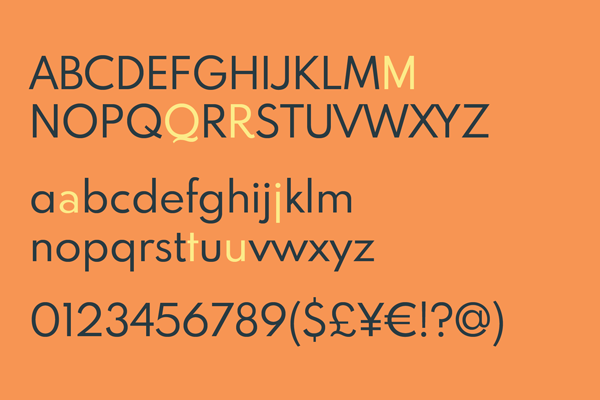
[Mitglied Vors…] Geschrieben November 9, 2019 Teilen Geschrieben November 9, 2019 Hallo! Wie findet ihr / gefällt euch die Drescher Grotesk? Ich würde sie gern für ein Cover (Ausmalbuch) verwenden, bin mir aber unsicher, da ich gelesen habe, dass sie manche wohl als Schrottschrift bezeichnet haben. Mir gefällt die Schrift jedoch sehr gut. Wem sie nicht gefällt: Was spricht gegen sie? Was mögt ihr nicht? Hier ein Link zur Ansicht: https://www.myfonts.com/fonts/bitstream/drescher-grotesk-bt/semi-bold/ Vielen Dank schon mal im Voraus! Gruß Peter Link zu diesem Kommentar
[Mitglied 1454…] Geschrieben November 9, 2019 Teilen Geschrieben November 9, 2019 Als Schrott hat sie – soweit ich weiß – nur Ulrich Stiehl von sanskritweb.net bezeichnet, da er die meisten Bitstream-Schriften als Schrott ansieht. Was gefällt dir denn nicht an ihr? Link zu diesem Kommentar
[Mitglied R::b…] Geschrieben November 9, 2019 Teilen Geschrieben November 9, 2019 Bitstream ist leider nicht gerade für hochwertige Digitalisierungen analoger Schriftentwürfe bekannt. Und wenn Du schon einmal an eine solche Anschaffung denkst, würde ich Dir wenigstens zu einer hinsichtlich Zeichenumfang und Schnittvielfalt besser ausgebauten Variante raten: Ein Schnitt der Standard-Version der Bauer kommt auf über 1.070 Zeichen und kostet 49,– €. Bei der Drescher von Bitstream stehen 55,–€ nur über 210 Zeichen gegenüber. Und man kann davon ausgehen, dass die formal-ästhetische Qualität eines FontFonts auch deutlich ausgefeilter ist. Wenn das Ausmalbuch speziell für Kinder gedacht ist, könnte man sich natürlich auch noch einmal mit diesem Thema beschäftigen: Eine ähnlich strenge Geometrische wie die Drescher, welche aber ein l mitbringt, das sicher besser vom I unterscheiden lässt und etwas kindlicher und sympathischer auf mich wirkt, wäre diese: Hinzukommt, dass sowohl die FS Lucas als auch die FF Bauer Grotesk ein großes ß (ẞ) enthalten. 4 Link zu diesem Kommentar
[Mitglied Uwe…] Geschrieben November 10, 2019 Teilen Geschrieben November 10, 2019 Hallo, die Drescher Grotesk ist nicht in den 1000 Bitstreamfonts, die mit Corel Produkten mitvertrieben wird, enthalten. Muss daher extra zugekauft werden. Der Hinweis mit dem schlechten Glyph/Preis-Verhältnis kam ja schon. Ansonsten finde ich die Schrift interessant und verweise mal auf weitere Informationen. Drescher Grotesk ist nur der Bitstreamname für die Super Grotesk? https://www.typografie.info/3/Schriften/fonts.html/super-grotesk-typoart-r85/ Da findest Du auch gut ausgebaute Versionen der Super Grotesk, so Du Geld ausgeben willst und kannst. Ich würde da aber noch mal in die Lizenzen reinschauen, wenn Du diese Schrift neu erwerben willst. Da gab es einiges an Änderungen in der letzten Zeit. Das wurde auch hier im Forum mehrfach angesprochen. Einige Lizenzen sind unbrauchbar. Daher habe ich mich schon früher auf die Suche nach kostenlose Alternativen zu Schriften wie der Super Grotesk gemacht. Mein Favorit wäre da die Spartan MB (320 Glyphen, SIL/OFL). https://www.fontsquirrel.com/fonts/spartan-mb Die sollte als Ersatz für die Drescher Grotesk vielleicht ausreichen? Oder wäre die Jost* (378 Glyphen, SIL/OFL) mit ihren alternativen Glyphen vielleicht interessant? https://www.fontsquirrel.com/fonts/jost MfG 3 Link zu diesem Kommentar
[Mitglied R::b…] Geschrieben November 10, 2019 Teilen Geschrieben November 10, 2019 vor 8 Stunden schrieb Uwe Borchert: Super Grotesk? https://www.typografie.info/3/Schriften/fonts.html/super-grotesk-typoart-r85/ Jepp, wenn keine Kursiven benötigt werden, könnte man sich noch die FF Super Grotesk mit über 600 Zeichen (darunter Titelsatzumlaute, Versalligaturen, diverse Ziffernsets und Alternativen für a und g) und zusätzlichen Condensed-Schnitten ansehen: 1 Link zu diesem Kommentar